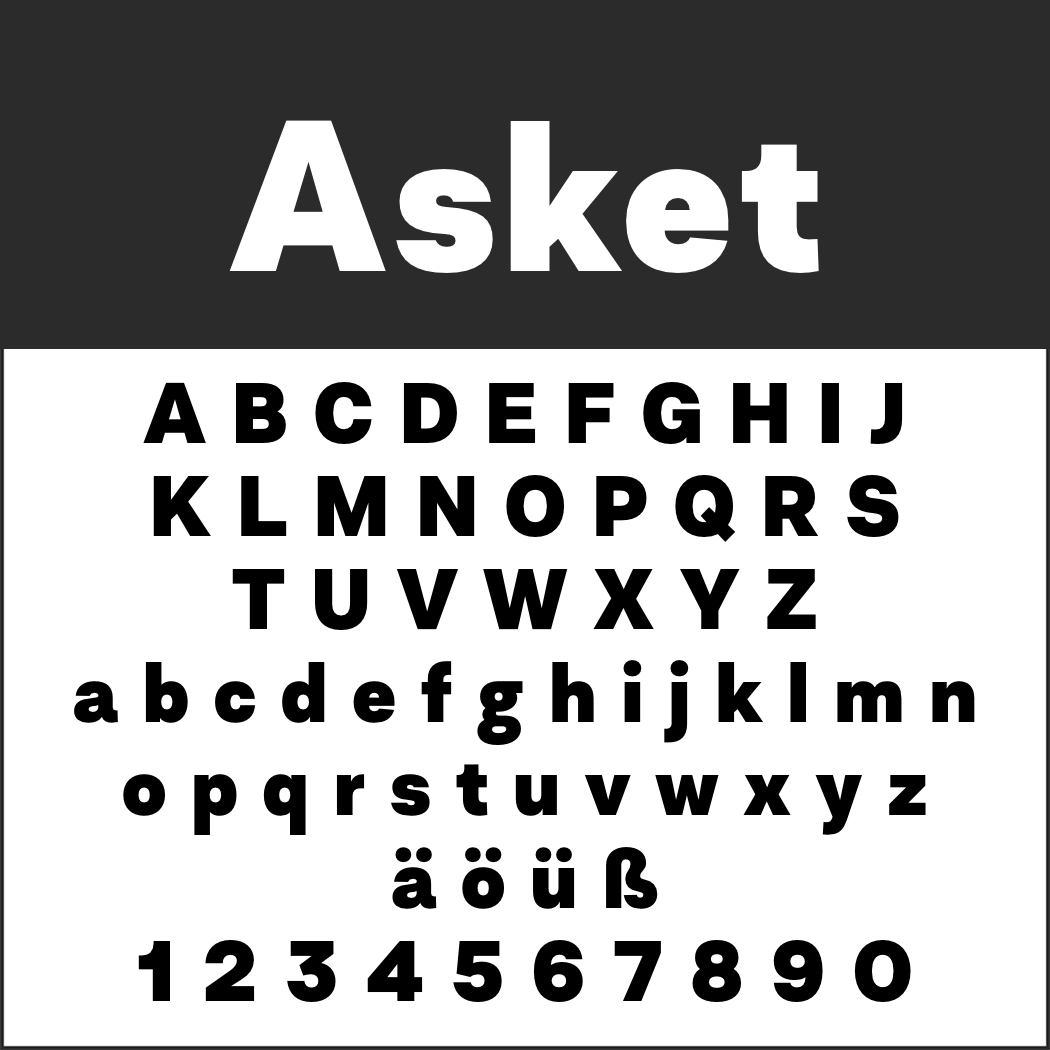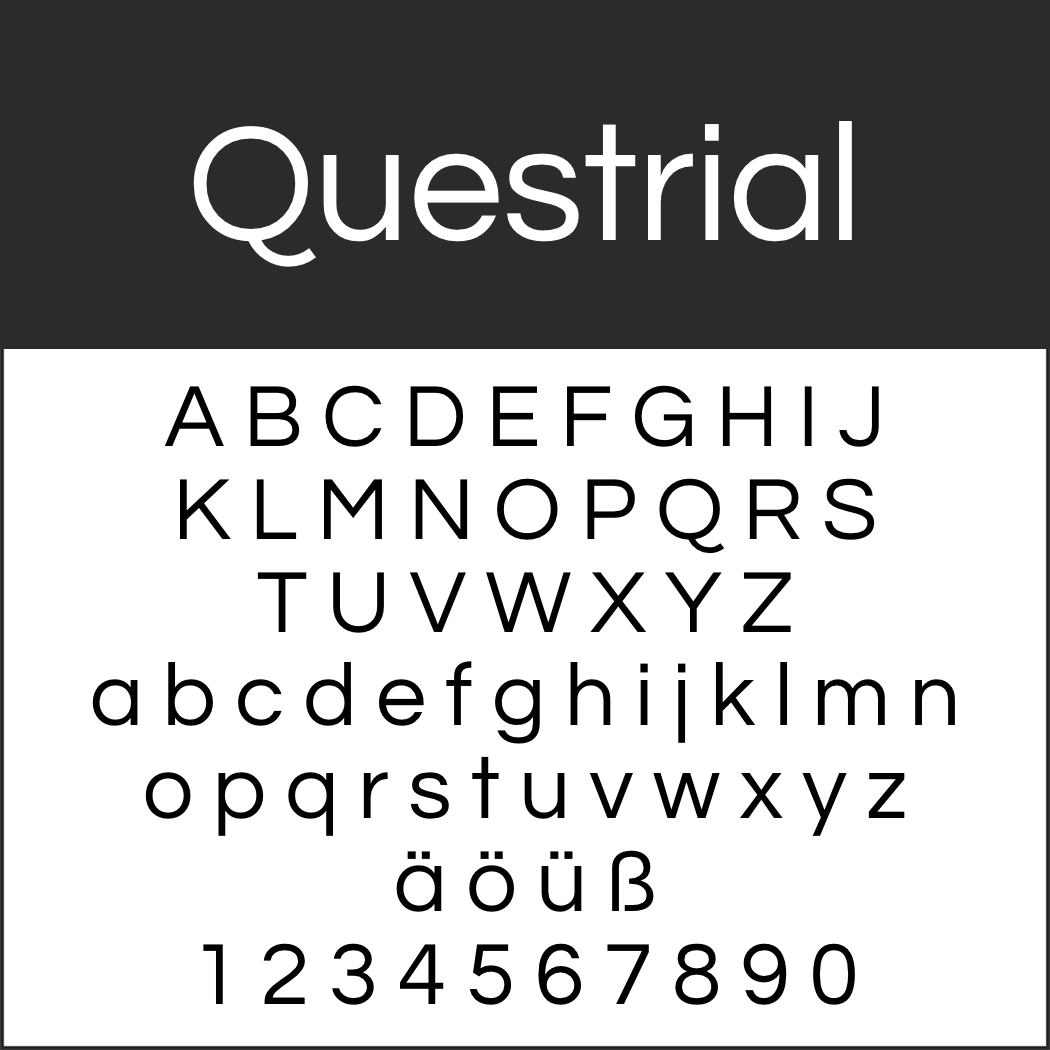
Was genau sind Standard-Schriftarten? Darunter verstehen nicht alle automatisch das Gleiche. PC-Nutzer denken wohl in erster Linie an die Schriften, die sich im Microsoft-Paket befinden. Es gibt aber auch Standards für Bewerbungen, wissenschaftliche Arbeiten und Zeitungstexte.
Standard-Schriftarten bei Betriebssystemen
Jedes Betriebssystem besitzt Standard-Schriftarten beziehungsweise Systemschriften. Microsofts Windows ist mit einem Anteil von nahezu 70 Prozent das weltweit meistgenutzte Betriebssystem. Folglich kennt auch nahezu jeder die mitgelieferten Fonts. Einer davon ist die von Microsoft festgelegte Standard-Schrift, die sich allerdings jederzeit ändern lässt.
Standard-Schriftarten bei Microsoft
Seit 2017 fungiert Calibri als die Microsoft-Standardschrift. 2021 kündigte der Software-Riese allerdings eine neue Standardschrift an. Von fünf vorausgewählten serifenlosen Schriften soll diejenige das Rennen machen, die bei den Nutzern am besten ankommt. Zur Auswahl stehen Tenorite von Erin McLaughlin and Wei Huang, Bierstadt von Steve Matteson, Skeena von John Hudson and Paul Hanslow, Seaford von Tobias Frere-Jones, Nina Stössinger, und Fred Shallcrass sowie Grandview von Aaron Bell.
Der große Vorteil generell von Microsoft-Schriftarten: Wegen der starken Verbreitung von Windows sehen viele Dokumente an einem fremden Bildschirm genauso aus wie beim Absender.
Von „websicheren“ Schriften zu Webfonts
Da es aber neben dem Platzhirsch Windows auch noch weitere Betriebssysteme gibt, musste man sich jahrelang mit einer kleinen Auswahl an Schriften begnügen. Diese sogenannten websicheren Schriften waren auf allen gängigen Betriebssystemen installiert. Dazu zählten unter anderem Arial, Times New Roman und Verdana. Eine nennenswerte Abwechslung oder gar Individualität war damit natürlich nicht möglich.
Mit der Verwendung von Webfonts erweiterte sich der Spielraum quasi unendlich. Denn ist der Font per CSS-Code eingebettet, muss die entsprechende Schrift nicht mehr lokal auf dem Empfänger-Rechner vorhanden sein. Der Browser lädt stattdessen die Font-Dateien von einem Webserver.
Standard-Schriftarten für bestimmte Bereiche
In der alltäglichen Geschäftspost haben sich die Standard-Schriftarten Arial, Times und Helvetica durchgesetzt. Experimente, die im schlechtesten Fall unseriös wirken, sind hier nicht angesagt. Vielmehr sollte Business-Korrespondenz formal der Norm entsprechen, wie Sie unter Aufbau Geschäftsbrief nach DIN 5008 nachlesen können.
Etwas weniger konventionell dürfen Schriftarten für Bewerbungen sein. Wie ausgefallen, hängt von der jeweiligen Branche und der zu besetzenden Stelle ab. Geht es um einen Job im Sekretariat, empfiehlt sich eher eine dort auch übliche Schriftart. Wer hingegen die vakante Stelle als Art Director ergattern will, glänzt eher durch ungewöhnlichere Fonts. Doch auch die sollten die üblichen Anforderungen erfüllen. Mehr dazu unter Die besten Schriftarten für Bewerbungen – seriös und gut lesbar.
Auch bei wissenschaftlichen Arbeiten kommen die üblichen Standard-Schriftarten zum Einsatz: Times New Roman, Arial und Calibri überwiegend. Während die Groteskschriften bei manchen Betrachtern eher „modern“ wirken, ist die Times New Roman dank ihrer Serifen bei langen Texten deutlich angenehmer zu lesen. Letztlich gibt es aber oft verbindliche Vorgaben für Schriftart und -größe durch Dozenten, Auftraggeber und Verlage.
Bei Zeitungen ist Times (nach der britischen Tageszeitung Times benannt) der Klassiker. Fließtexte sind zwecks der besseren Lesbarkeit auch heute meist in einer Serifenschrift gedruckt, Überschriften, Subheadlines und Vortexte gerne auch in Groteskschrift. Näheres zu diesem Thema lesen Sie unter Schriftart Zeitung – kostenlose Fonts für die tägliche Lektüre und vieles mehr.
Gratis-Fonts, die wie Standard-Schriftarten aussehen
Kleine Abwechslung gefällig? Oder die Standard-Schrift steht aus irgendeinem Grund nicht zur Verfügung? Für alle Fälle zeigen wir Ihnen hier ein paar Ausweichmöglichkeiten.
Ähnlich wie Standard-Schriftarten ohne Serifen
Standard-SchriftartenCarlito
Carlito basiert auf der Schrift Lato und ist metrisch kompatibel mit Calibri.
Freeroad
Freeroad kann als Alternative zu Arial oder Helvetica zum Einsatz kommen.
Standard-SchriftartenQuestrial
Questrial besitzt einige Elemente der Helvetica.
Liberation Sans
Die Designer konzipierten den Font als Ersatz für Arial und Helvetica.
Standard-SchriftartenAsket
Was hier so dick aufgetragen aussieht, gibt es auch in einer dünneren Light-Version.
Tinos
Tinos sieht aus wie Times New Roman und wurde zudem für den Bildschirm optimiert.